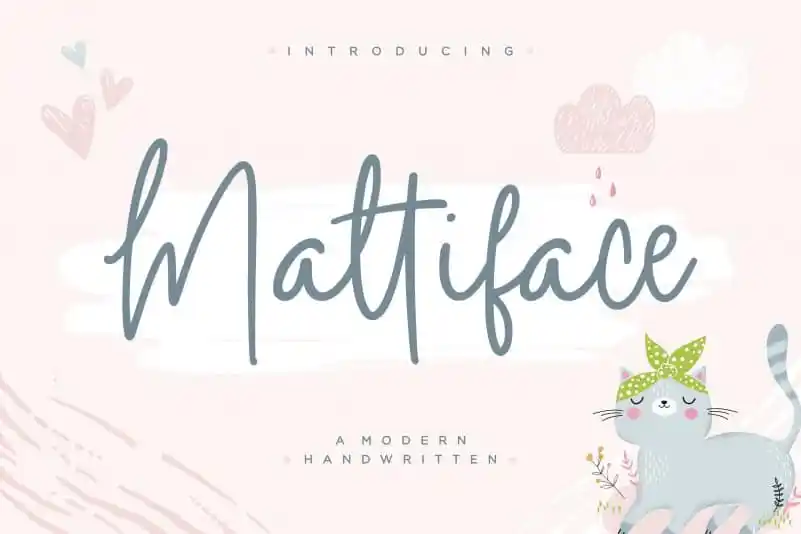
Mattiface Modern Handwritten Font – Download Grátis
A fonte ‘Mattiface Modern Handwritten Font’ é perfeita para diversos projetos gráficos criativos. Seja para adicionar um toque pessoal e único em embalagens de produto, criação de marca ou publicidade em megazines, ou mesmo para expressar mensagens sobre redes sociais e eventos como casamentos, este fonte moderna e retrô oferece uma textura única que se adapta perfeitamente ao estilo elegante e sofisticado da letra escrita a mão. A designer balpirick criou um recurso gráfico único que combina elementos de design minimalista com detalhes autênticos, proporcionando resultados profissionais sem perder o espírito pessoal tão importante para muitos projetos de identidade visual e design editorial. Usar essa fonte é uma ótima maneira de expressar seu pensamento através de um design visual único e envolvente.